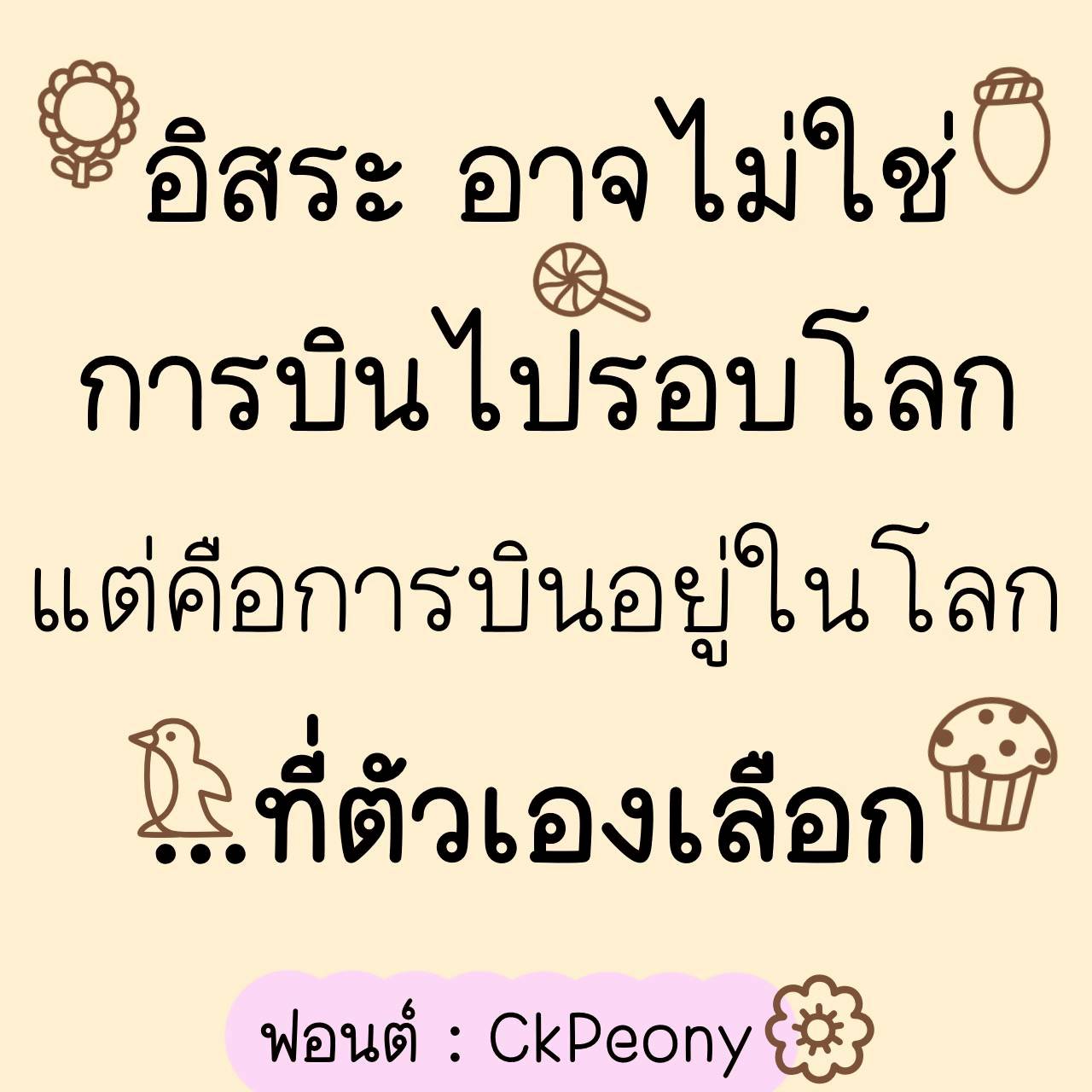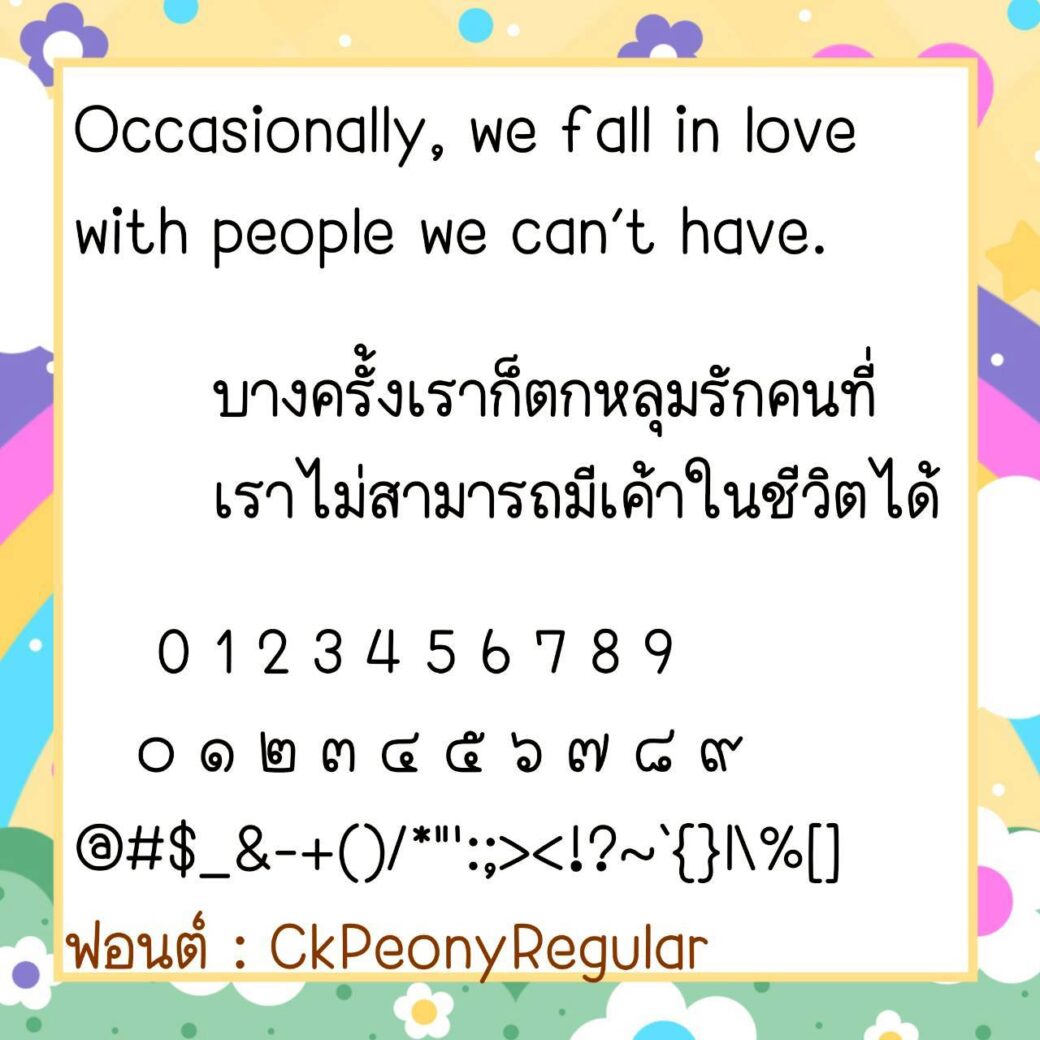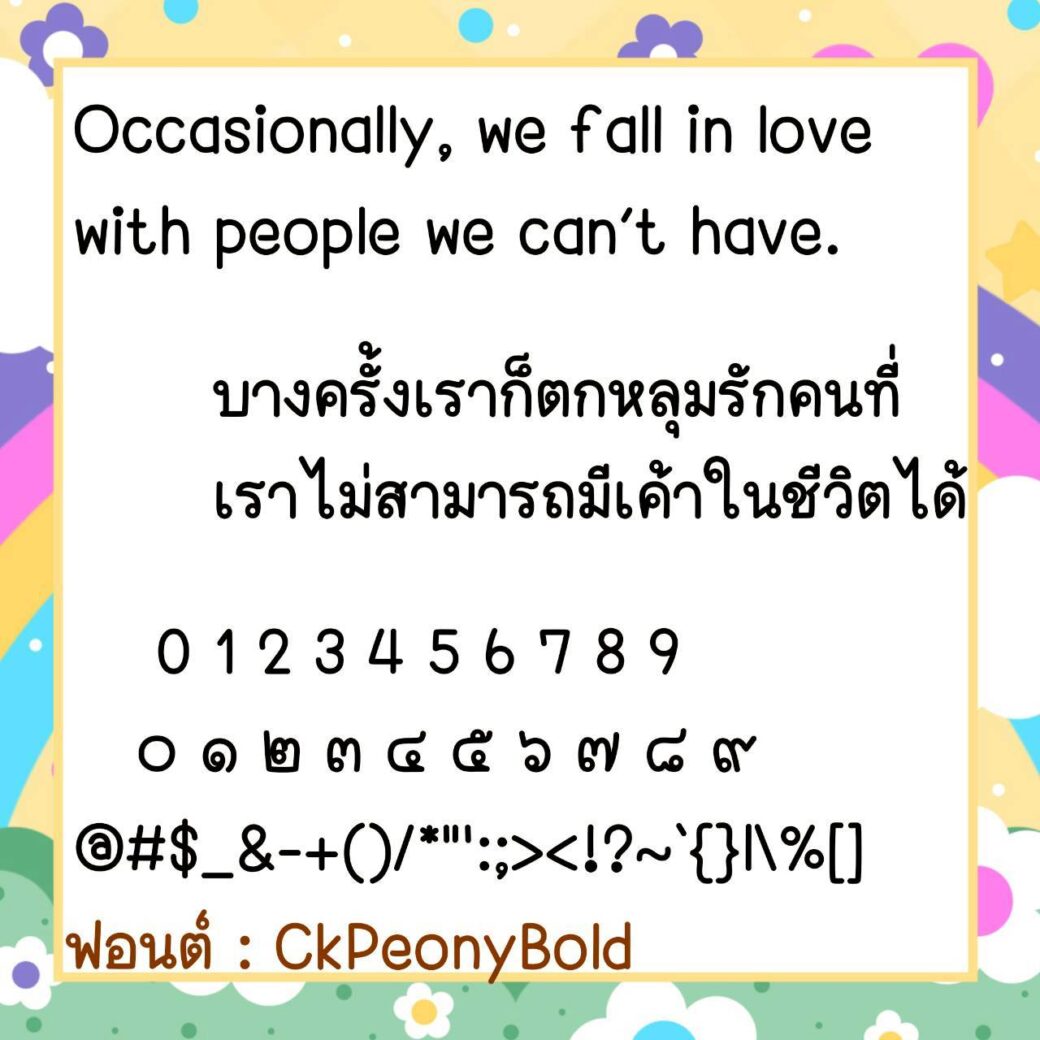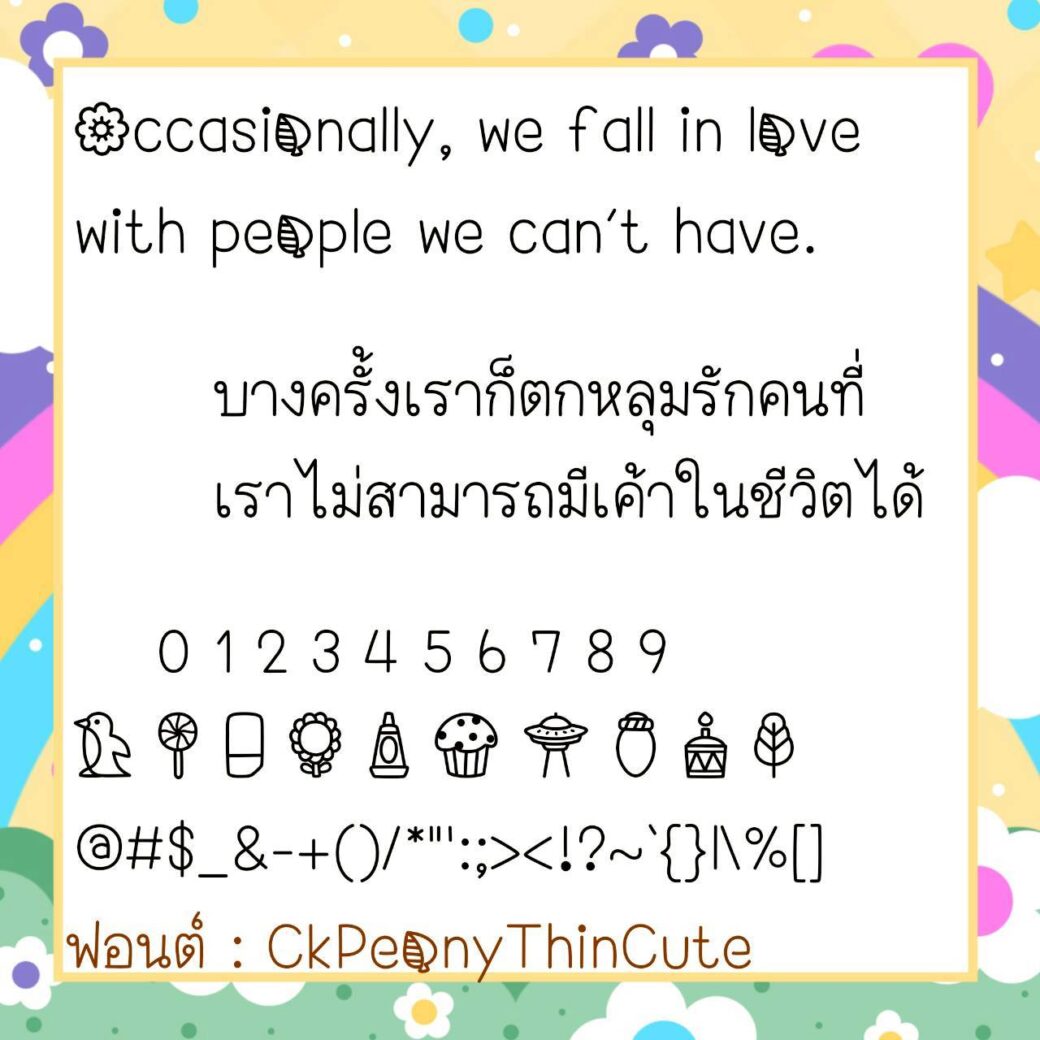
Font CkPeony
🔸 ฟอนต์ลายมือแนวเป็นระเบียบ ดูมีความกึ่งเรียบร้อยแต่ก็มีความน่ารักในตัว เน้นอ่านง่ายสบายตา และยังมีไฟล์อิโมจิน่ารักๆ ที่ใช้แทนเลขไทยให้ด้วยค่ะ 🥰💙
🔹 The handwritten font is neat and tidy, looks semi-neat but also has a cuteness to it. It emphasizes easy reading and is easy on the eyes. There is also a file of cute emojis that can be used instead of Thai numbers. 🥰💙